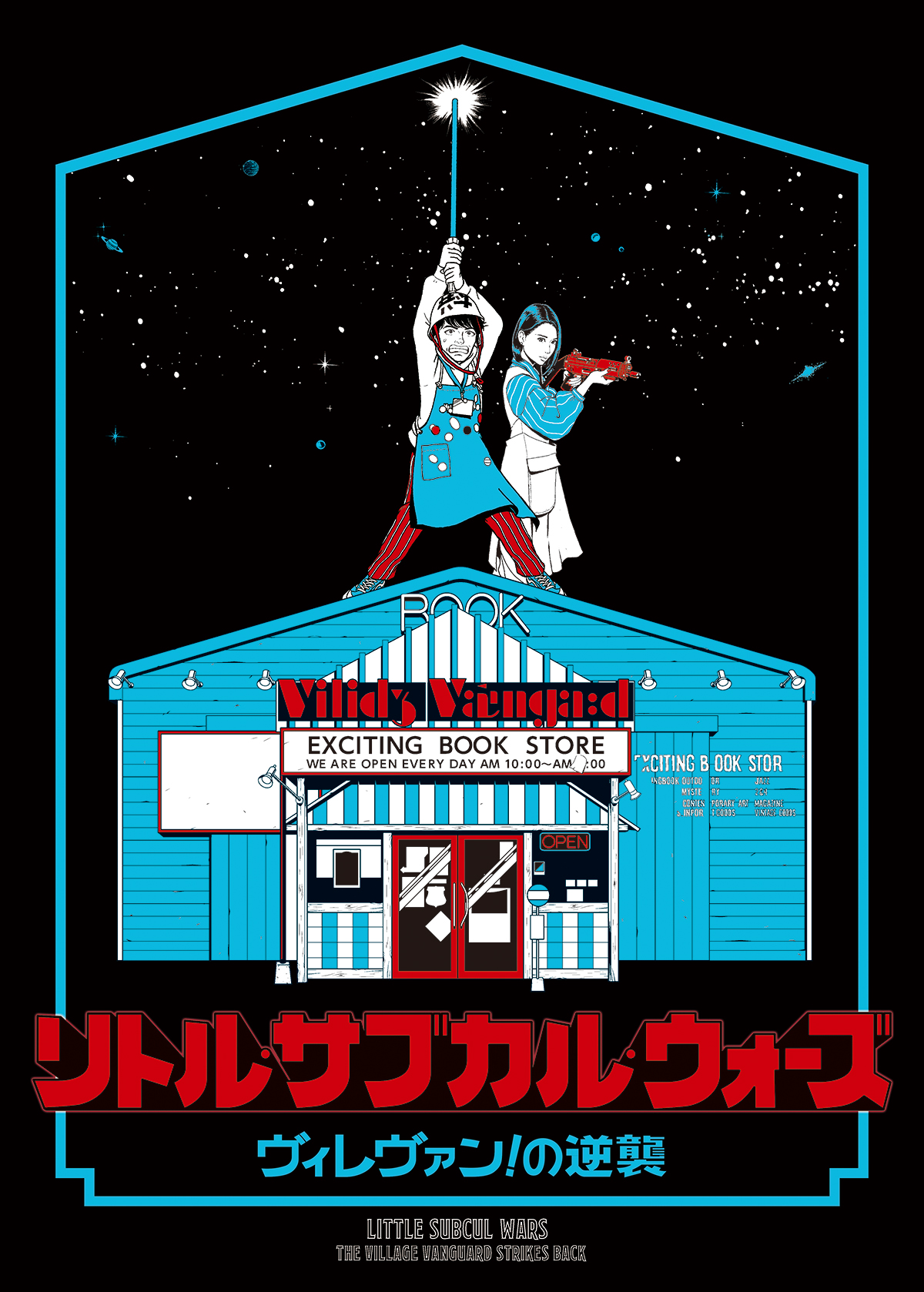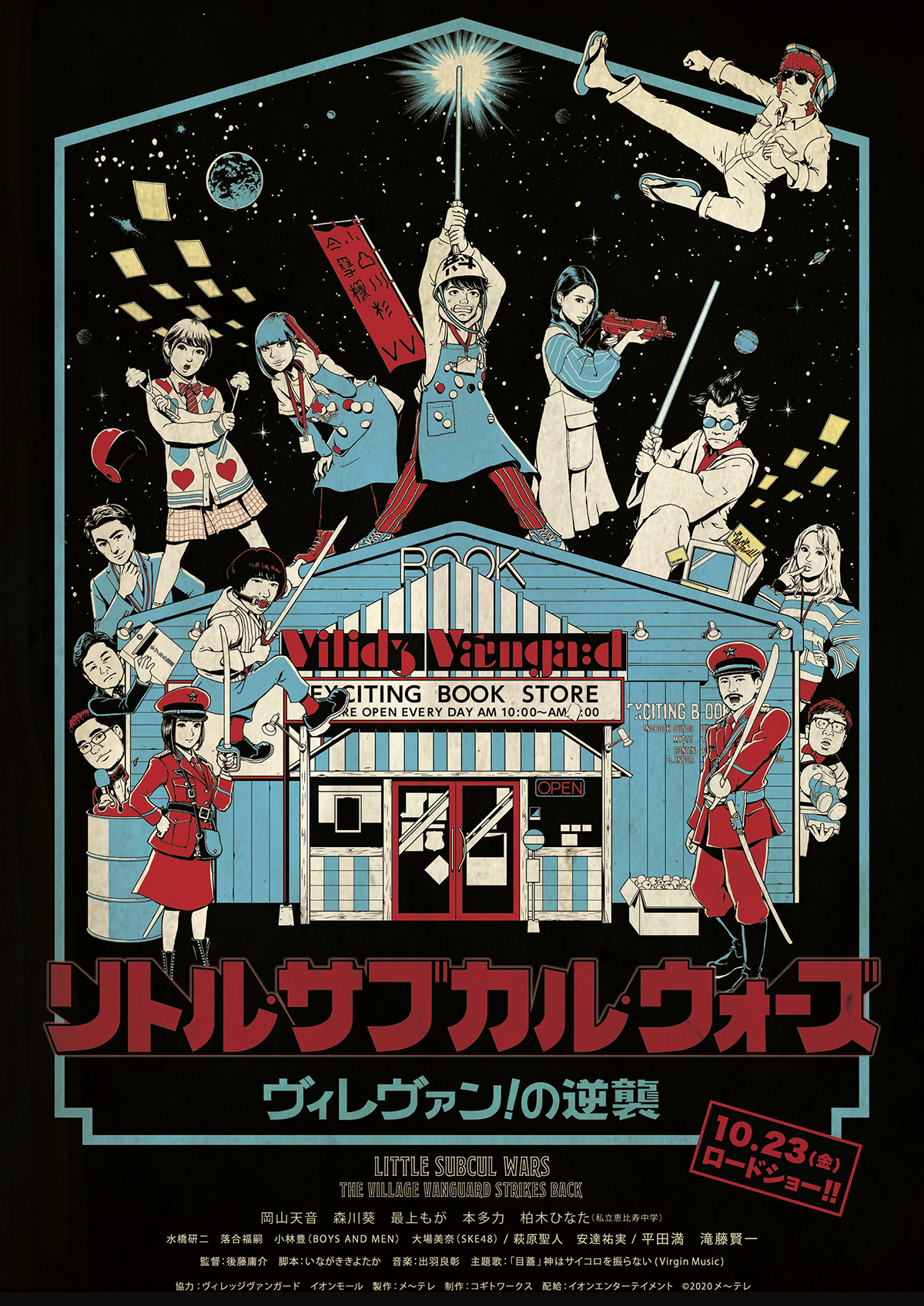
今回は映画『リトル・サブカル・ウォーズ ~ヴィレヴァン!の逆襲~』のポスターのフォントをご紹介。本記事はデザイン構成において重要な「フォント」の選定プロセスや加工方法を、貴重なプロの実例から紐解いてデザイン制作に役立てる連載です。
アンバランスさを意識した文字で懐かしさを演出
“遊べる本屋”をコンセプトにした複合型書店「ヴィレッジヴァンガード」を舞台に、自称「空っぽ」の杉下とその仲間たちのハチャメチャで刺激的な青春の日々を描いたドラマシリーズ「ヴィレヴァン!」の劇場版『リトル・サブカル・ウォーズ ~ヴィレヴァン!の逆襲~』(監督:後藤庸介)。この世から “サブカル” がなくなっていることに気づいた杉下らが、それを取り戻すべく壮絶なバトルを繰り広げます。
ポスターでは、サブカル愛に溢れた作品世界が、名作SF映画へのオマージュを思わせるメインビジュアルと、その同時代性を意識しつつも新しさを取り入れたデザインやタイトルロゴなどで表現されています。
Font.01「オリジナル」
作り起こしの文字で懐かしさを感じさせる
本作は、70年代にシリーズ第1作が公開された名作SF映画へのオマージュ要素が強い内容で、タイトルにもそれが現れているため、タイトルロゴもその同時代性を意識して作り起こされました。その際、既存フォントでは出せないようなアンバランスな文字にすることで、懐かしさを演出する工夫がされています。下図はその制作工程。ベースの文字やその奥行きなどを設計したあと、立体的に飛び出して見えるようなロゴが作成されました。
Font.02「オリジナル」
メインタイトルと同じコンセプトの文字に
サブタイトルはメインタイトルと同じコンセプトで、どこかアンバランスで懐かしさを感じさせる文字が作り起こされています。下図はその制作工程です。メインタイトルより文字サイズが小さくなるため、ふところを広く取ったり、濁点の位置を調整するなどして視認性が高くなるような工夫もされています。
Font.03「Mortuary Deco BB」
洗練された書体でメリハリをつける
タイトルの欧文は、袋文字風のデザイン書体「Mortuary Deco BB」(Blambot)に。メインタイトルやサブタイトルとは逆の洗練された雰囲気の書体を使うことでメリハリをつけ、バランスをとる工夫がされています。